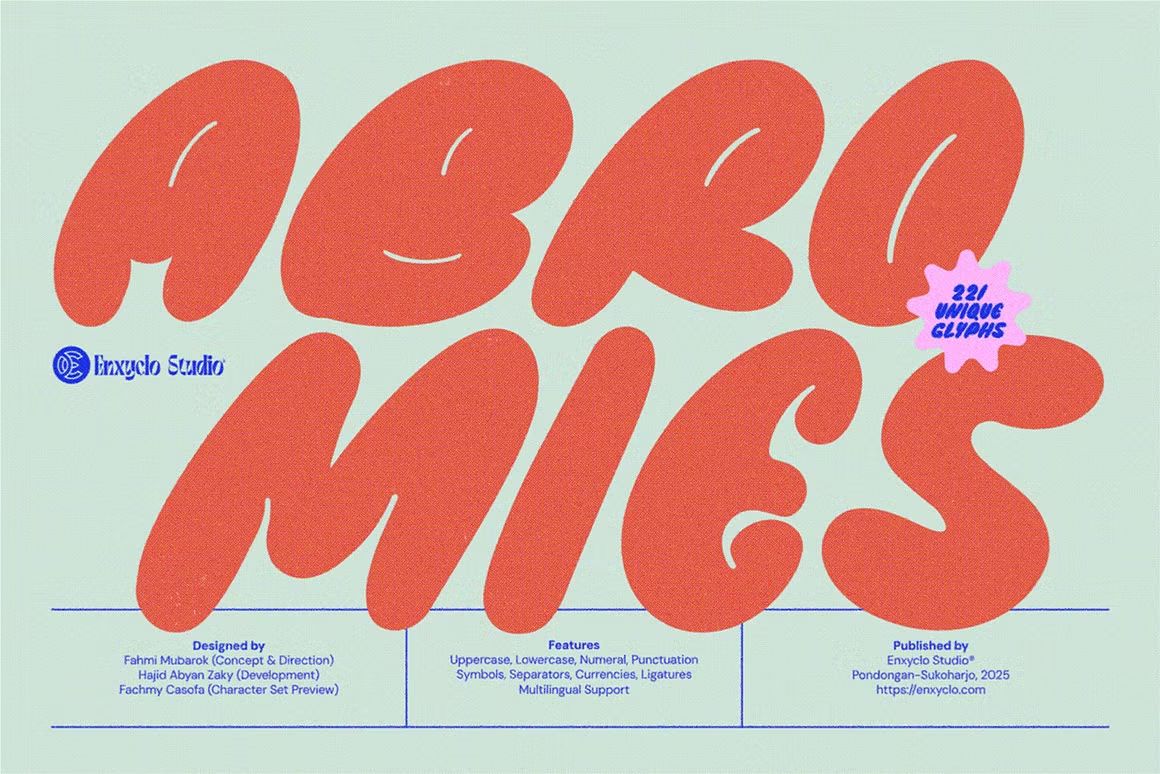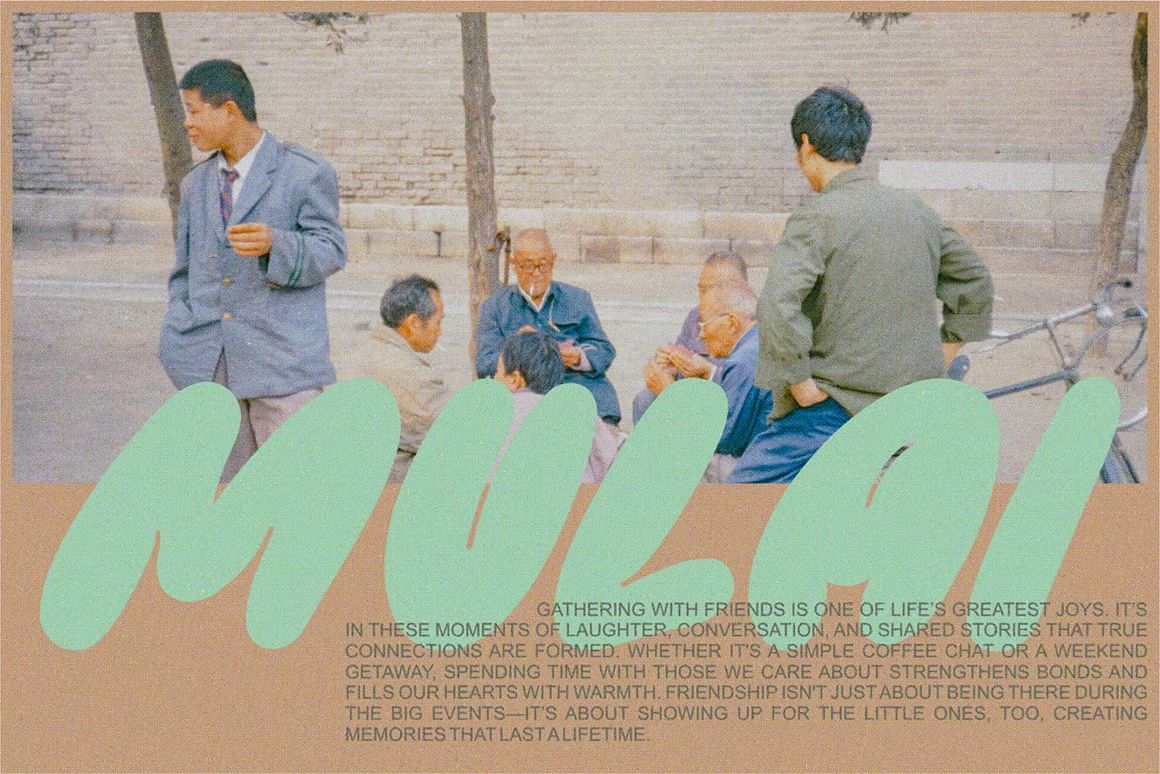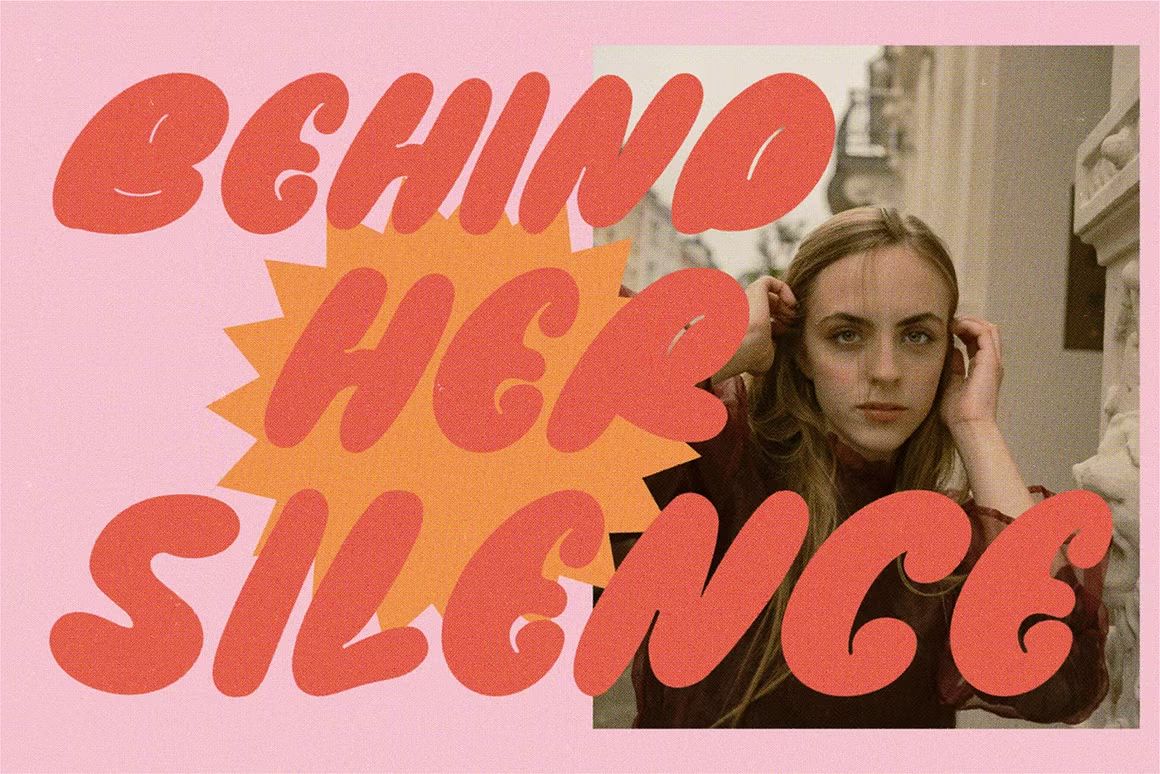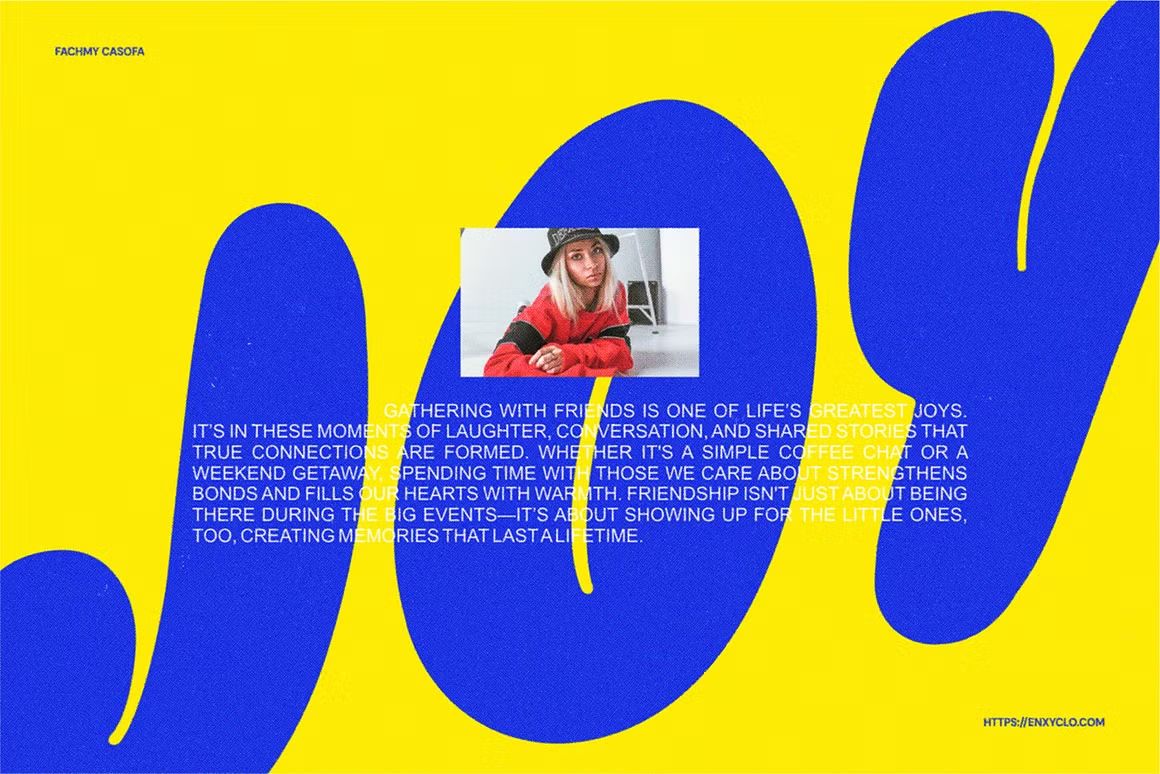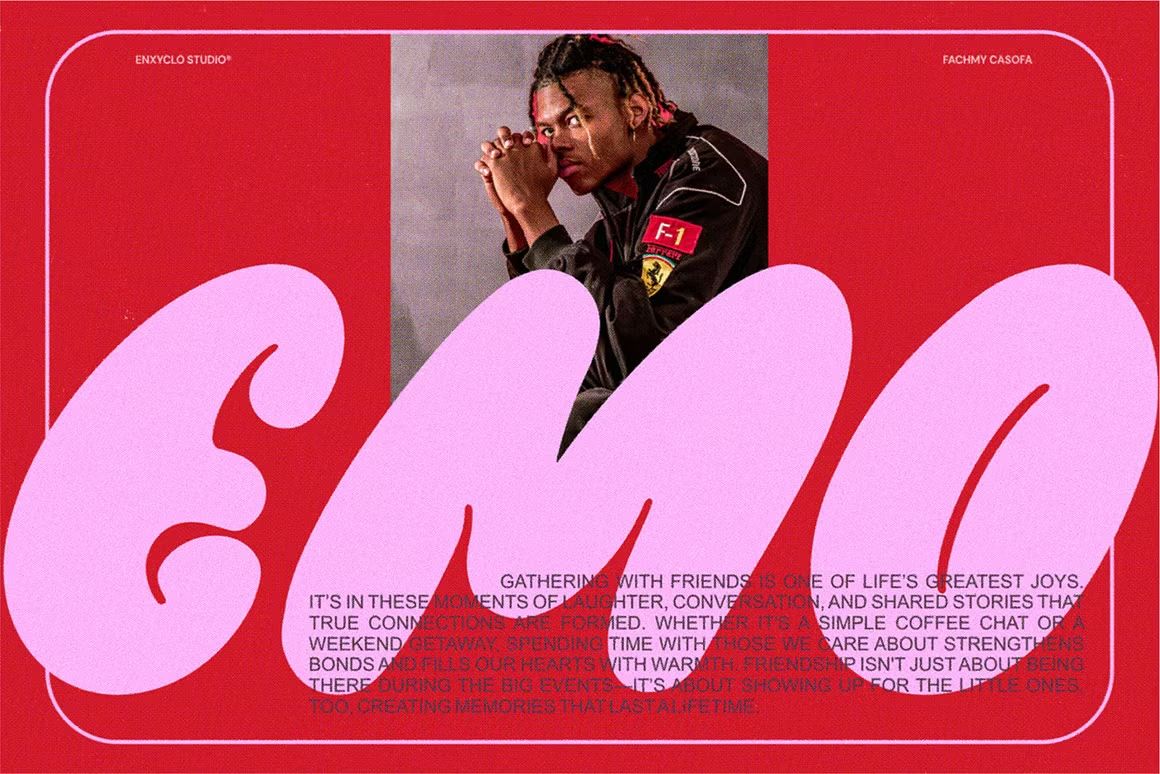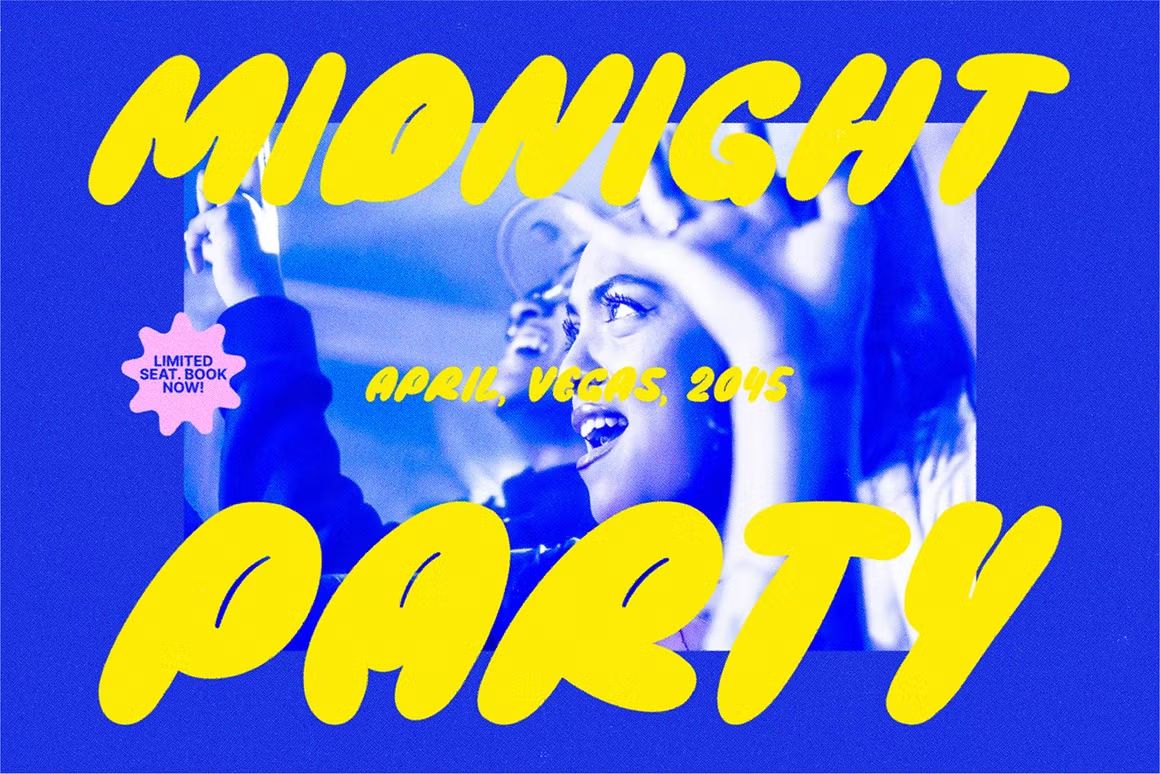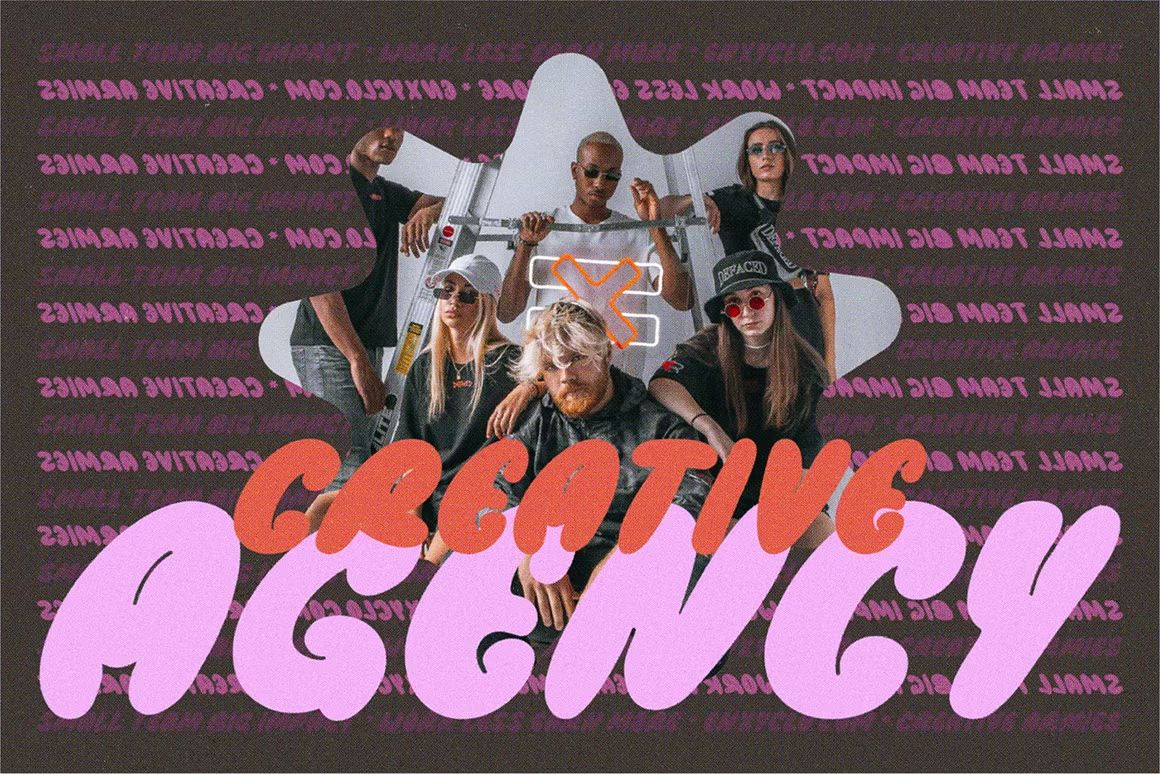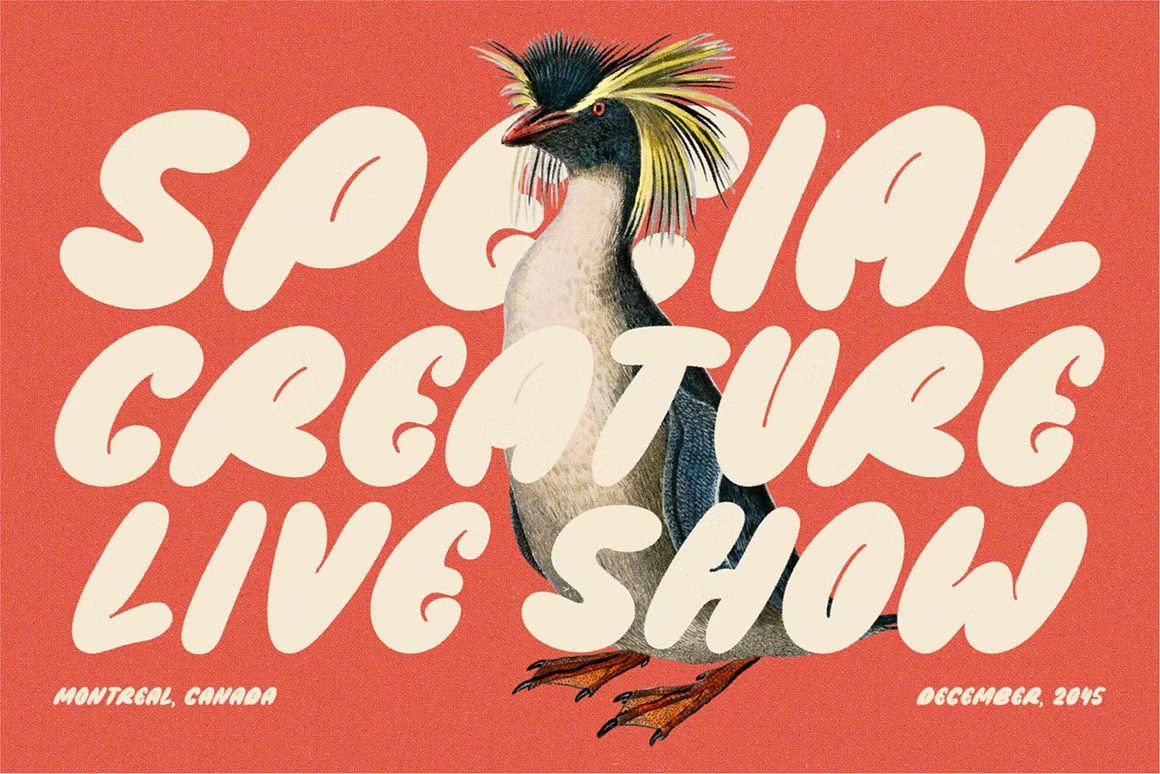
Abromies – Handwritten Font
Abromies adalah font handwritten kasual dan bersih, cocok untuk quotes, journaling, dan desain personal. Format OTF/TTF/WOFF, siap digunakan.
Abromies adalah font handwritten dengan gaya santai, halus, dan natural—menyerupai tulisan tangan sehari-hari yang bersih dan bersahabat. Cocok digunakan untuk journaling, kartu ucapan, branding personal, quotes, dan konten media sosial. Abromies memberi sentuhan personal yang hangat dan ringan dalam setiap desain, tanpa kehilangan keterbacaan.
• Handwritten font bergaya kasual dan natural
• Ideal untuk journaling, quotes, dan branding personal
• Termasuk huruf kapital, kecil, angka, dan simbol